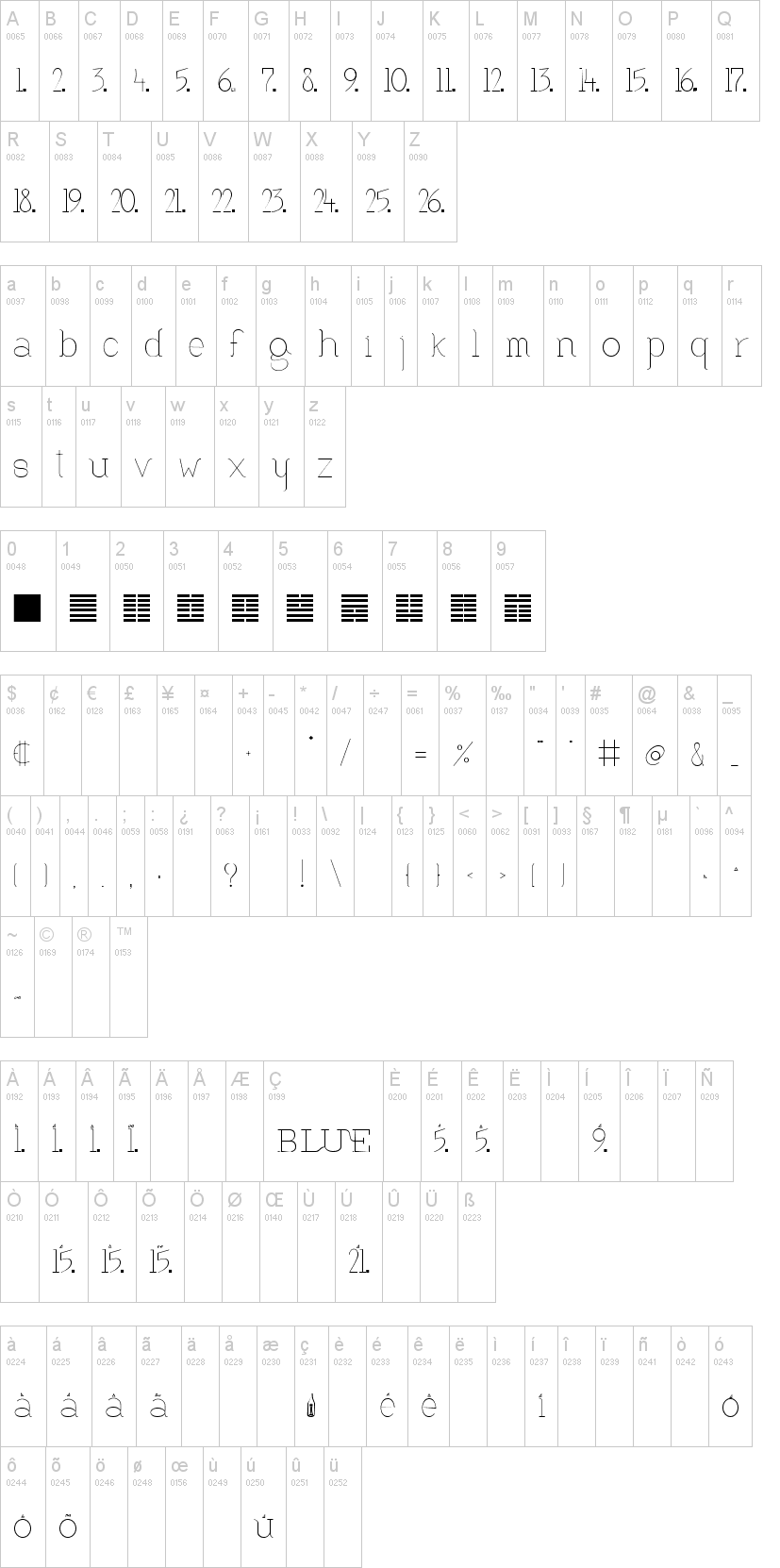
Note of the authoresta fonte foi criada em inspiração ao projeto musical iamamiwhoami. a caixa alta dessa fonte é numérica, cada letra corresponde ao seu lugar na fila dos alfabétos, logo a letra A será 1. e F será 6. os números de 0 a 9 são simbolos do I Ching, livro dos Hexagramas, segundo a teoria utilizada nas preludes que antecediam o primeiro disco da banda. com conceitos da era bounty e seus códigos secretos nos títulos da música, até as grandes ondas azuis de blue nas serifas da fonte, to whom it may concern type é uma tipografia totalmente experimental. para ser usada em tamanho de corpo menor que 24 será necessário uso de stroke ou contorno na mesma para que fique legível. não use efeito bold ou italic, os mesmos podem destorcer a fonte. criada e vetorizada por mim, designer, felipe. para quem se interessar!